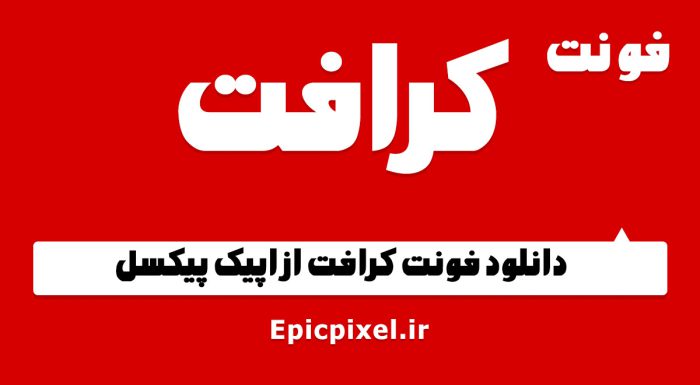
دانلود فونت Craft فارسی Font کرفت رایگان |
فونت کرافت یا همون کرفت مناسب اون طراح هایی هست که میخوان یه متنی رو بصورت درشت توی طراحی شون استفاده کنن. ناگفته پیداست که این فونت بدرد کارت ویزیت نمیخوره اما برای اینکه بین یه عالمه متن و عکس، یه متنی بولد و تو چشم باشه فونت فارسی کرفت عالیه